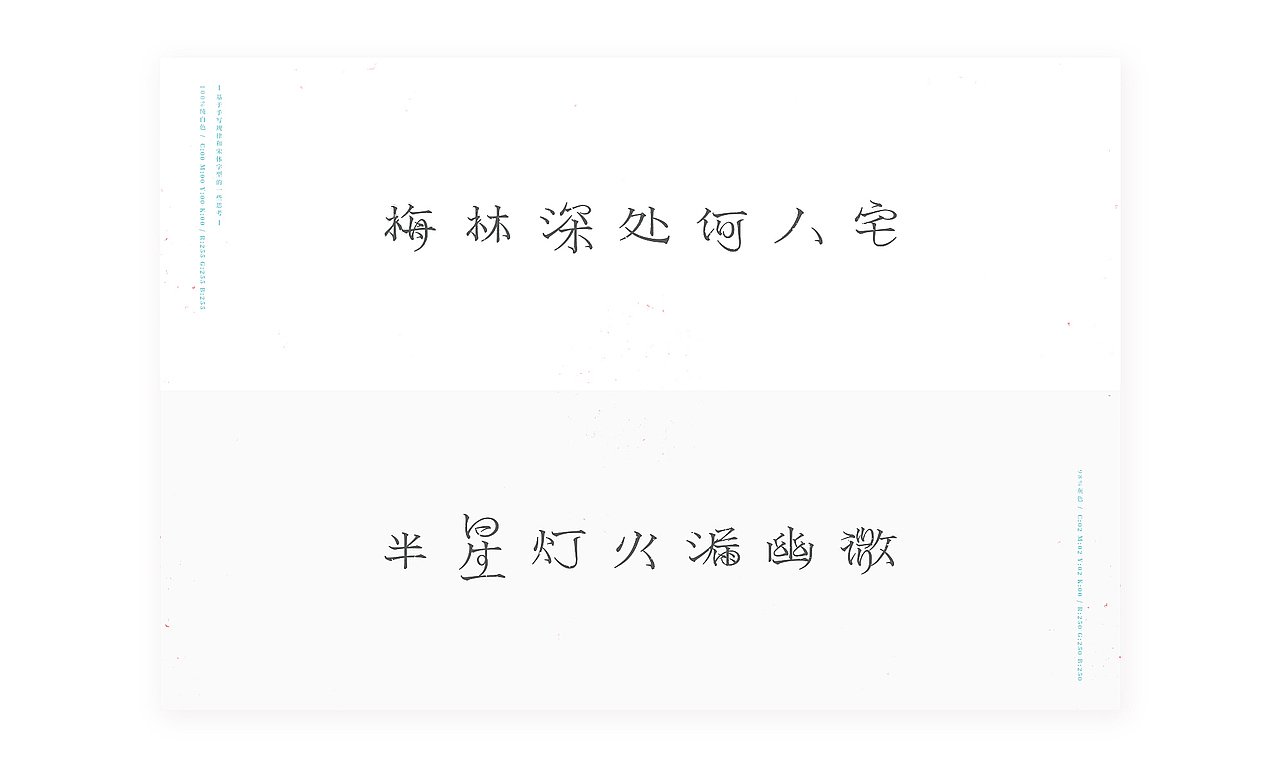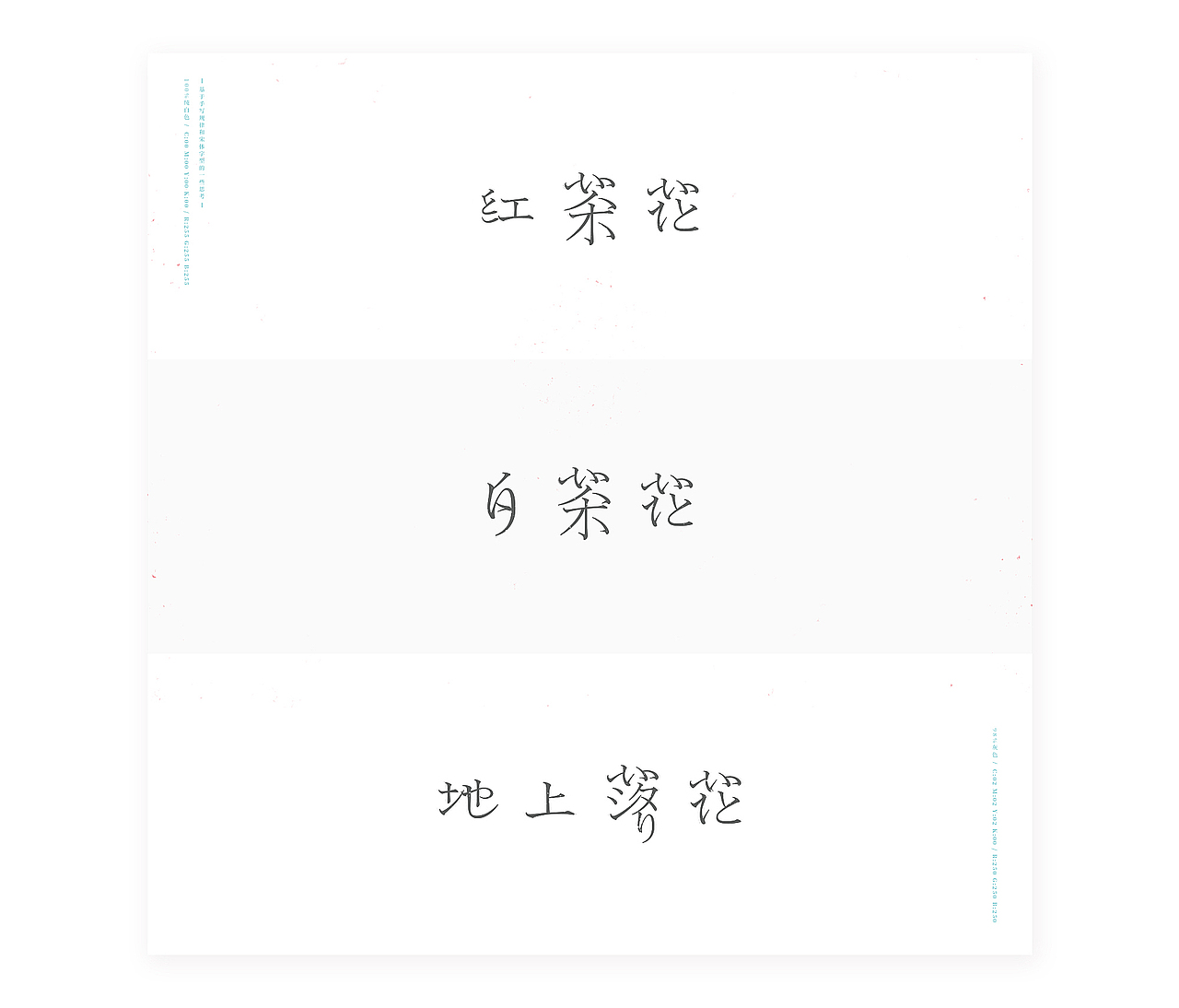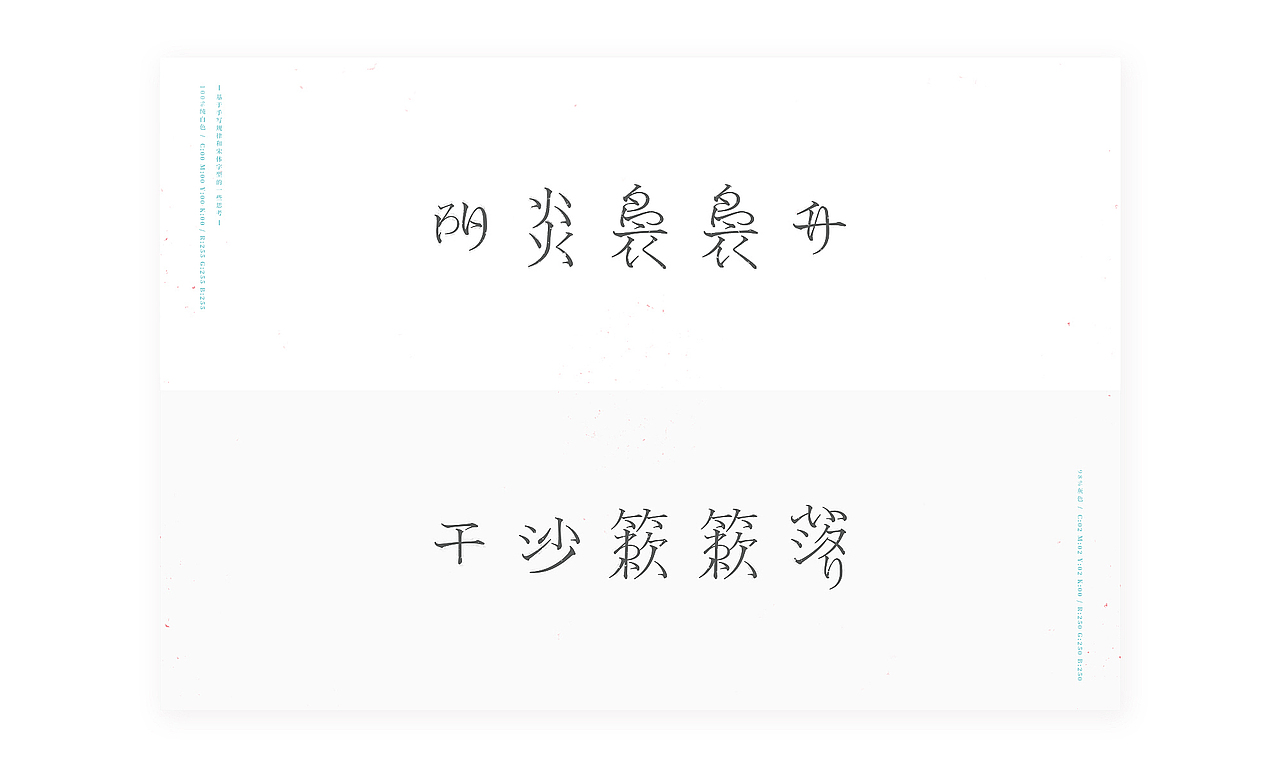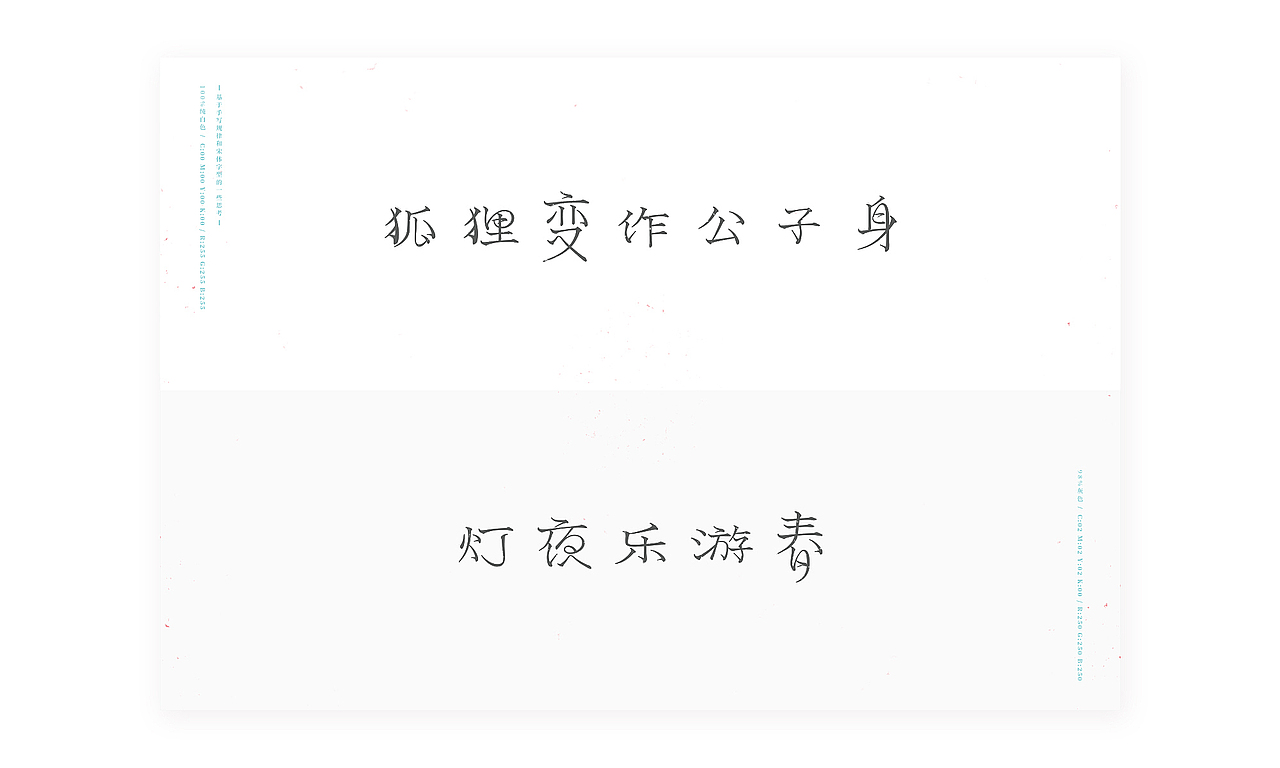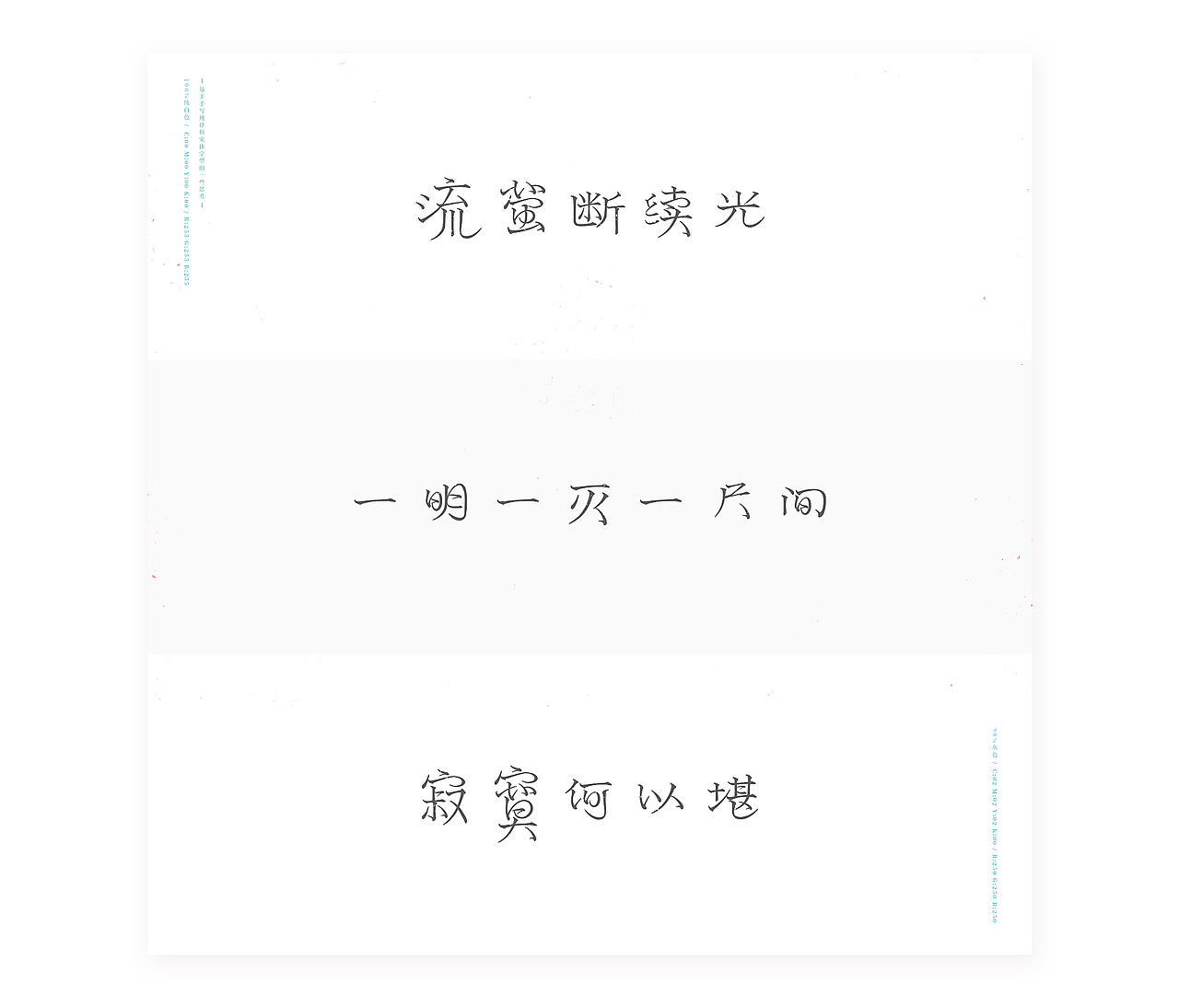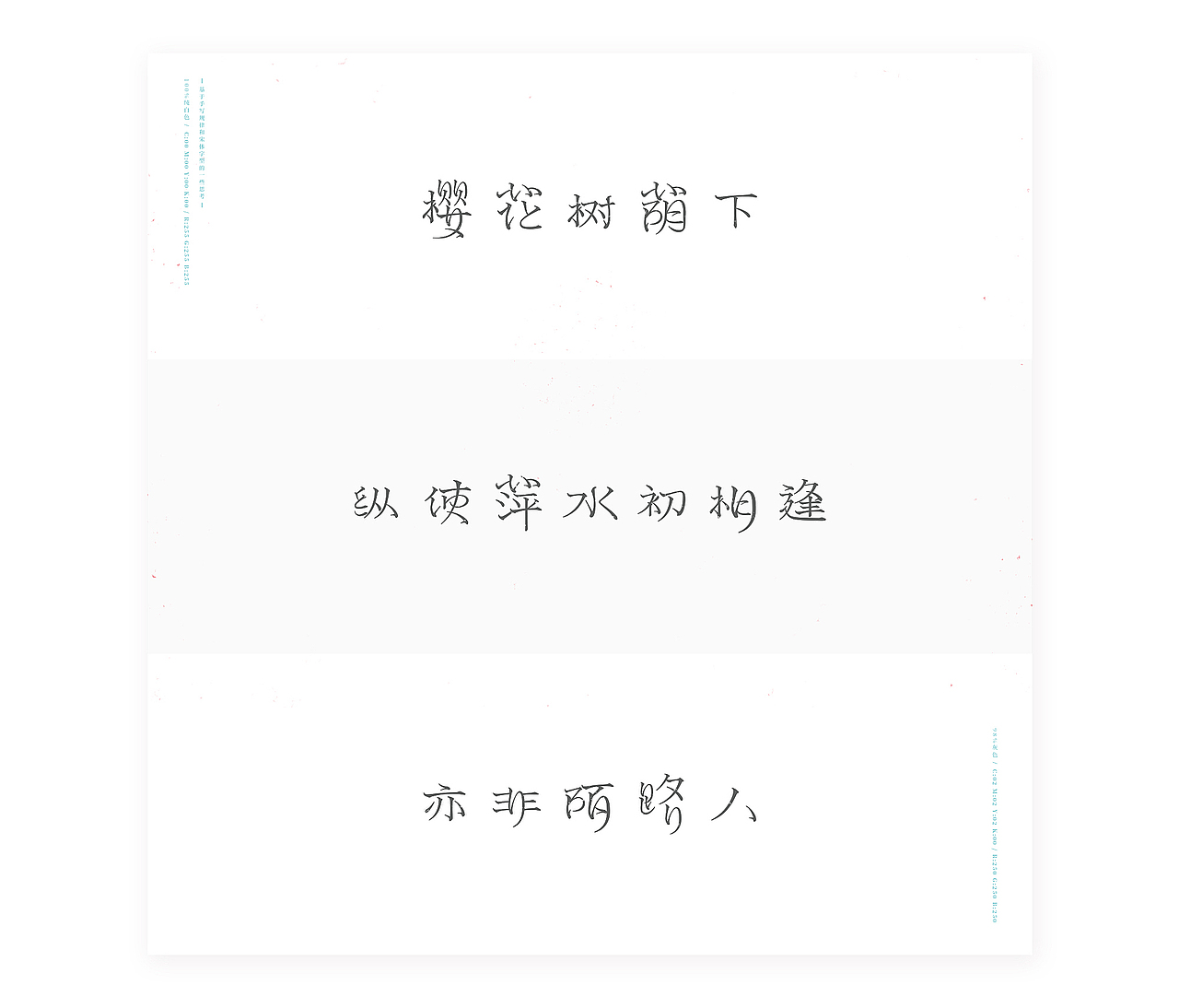
基于手写规律和宋体字型的探索
自旧字体设计之后有了全新的尝试,此篇字体设计源于手写规律以及宋体字型的一些思考,在创作过程中探索宋体字型和手写规律存在的联系,初学者应该知道,字体设计最好遵循手写规律,也就是平时怎么写字,横竖撇捺怎么摆放,字体设计就遵循这样的规则能让人更加容易识别和接受,这是我对字体设计的一点认识。而宋体字给我的感受是既复古又清新,我很喜欢宋体。这篇字体设计同时结合这两点,既清新隽永又不木讷呆板,字体笔画多样多变,不同笔画组成的每一个字的效果给人感觉都不尽相同,享受字体给我带来的舒适的快乐,最终结果让我感到惊喜。
这篇字体设计的内容是一些俳句,贴近生活,有些平凡有些直击心灵。由于句式有点长,所以分上下两句,每一页是一句完整的俳句。希望跟大家交流。